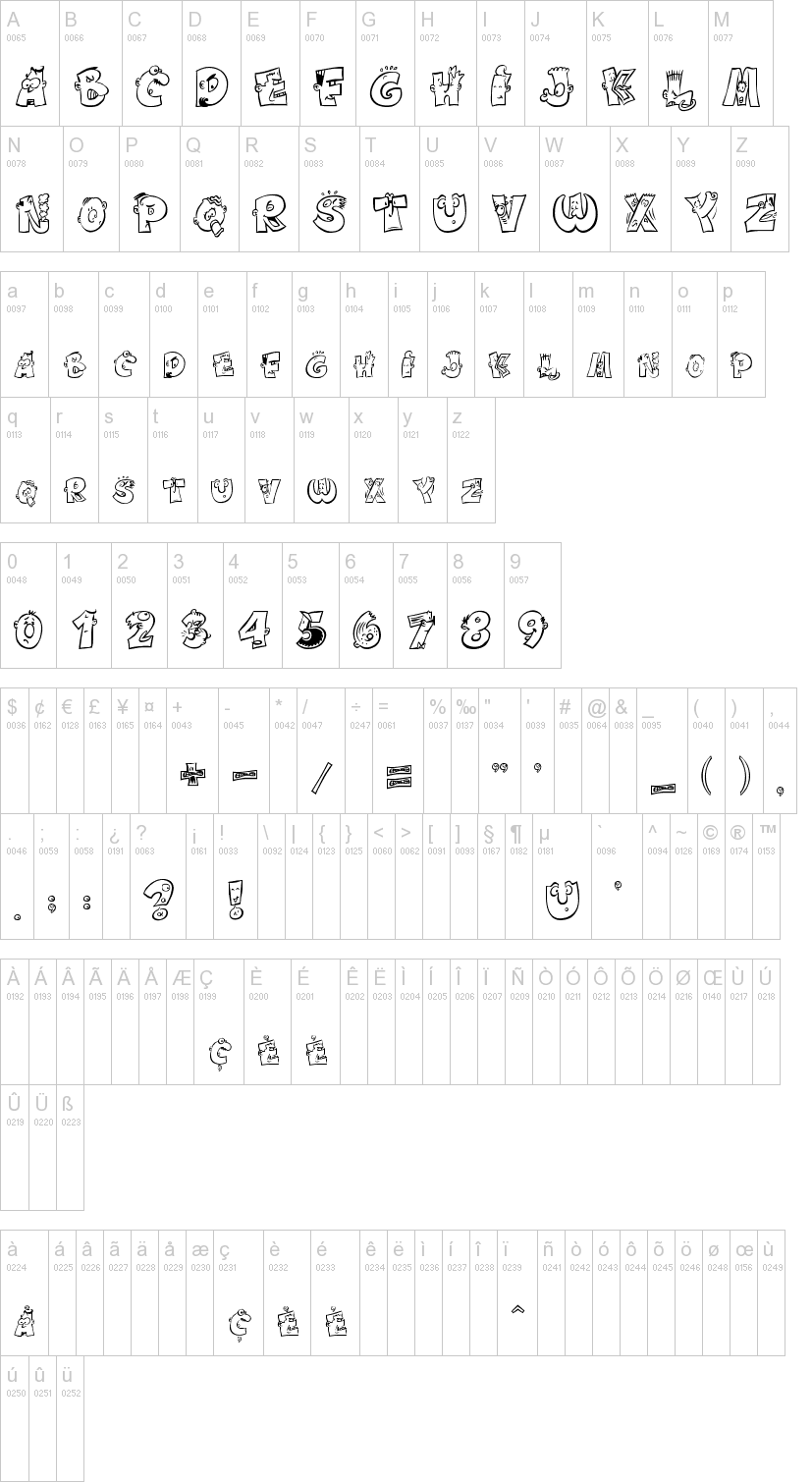
Caricature
Caricature 是一款英文字体,它具有活泼、有趣的设计,可以用来制作漫画、插图、海报等。它的字体特征是粗细不均,字母之间的间距较大,而且字母的形状也有所不同,使用它可以让文字更加有趣、生动。
Caricature是一款非常不错的手写艺术字体,具有很好的视觉感,适合于文化类的宣传设计、商业类品牌的广告和产品包装设计以及个性化文字排版等较多场景。